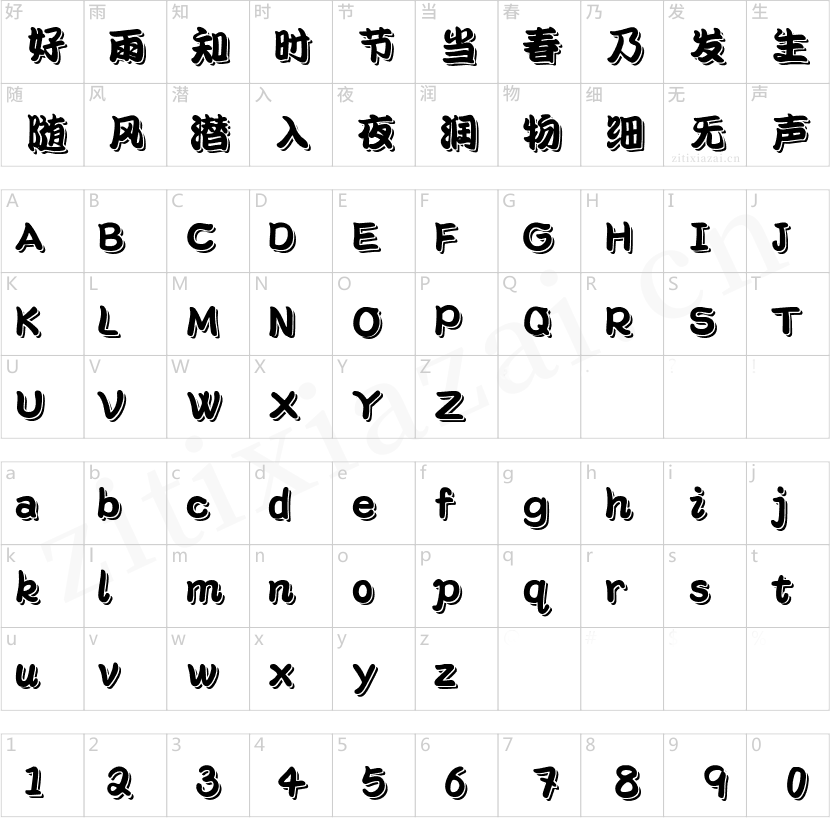
妙笔江户川新风体
妙笔江户川新风体,这款字体结构工整、笔画清晰,兼顾美观与易读性,适用于标题、正文、海报、包装、LOGO 等多种场景。字形优雅稳定,风格百搭耐看,适配日常排版与创意设计,让文字呈现更舒适、更具质感。妙笔江户川新风体一笔一画,皆是细节,以均衡的比例、流畅的线条打造舒适视觉体验,字形端正大气,风格简约现代。无论是商业设计、品牌宣传还是日常排版,都能轻松驾驭,让文字更有格调与力量。妙笔江户川新风体字体下载。
字魂字体妙笔江户川新风体字体是由字魂创意字库设计并生产的一款可商用的字体,被收录于妙笔AI系列。该字体支持GB-2312标准,包含7299个中文、字母、符号和数字,字体类型偏向创意字体,具有活泼、动漫、可爱、时尚的风格,在市面上广泛用于教育培训、广告、印刷品&包装等场景。